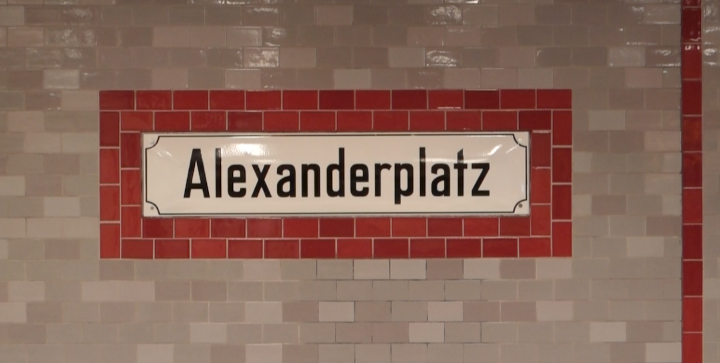
Welche Schrift ist das? (Alexanderplatz)
die wird es so als schrift nicht geben (und schon gar nicht als font). weil vermutlich seinerzeit mit schablonen handgefertigt.
du kannst aber nach ähnlichen suchen. zum beispiel eine, die hier vor einiger zeit quasi gemeinschaftlich entstanden ist:
Meine Freunde machen gerade dort im U-Bahnhof eine Ausstellung und ich wollte Ihnen bei der Typo behilflich sein,
sie brauchen das Wort Berlin (Alexanderplatz) - ich seh mich schon zeichnen.....
wie bereits angemerkt handelt es sich um eine typische Konstruktion wie man sie speätestens ab den 1920ern her kennt. So was gibt es auch auf Straßenschildern der Prä-Din1451-Ära und vielen anderen Orten.
Das kleine a ist allerdings extrem verschieden.  Es gibt hier vor Ort mindestens drei Versionen des kleinen a. Schleife geaht nach unten, wagrecht oder nach oben in den Schaft. Nur wenige Meter von hier findet man an einer Kreuzung an den verschiedenen Straßenschildern alle drei Versionen. Ich habe mich für die am strengsten geometrisch wirkende Version entschieden.
Recht dicht dran, wenn auch hier nicht ganz genau, möglicherweise sogar der DIN1451 Vorläufer der Preußischen Eisenbahnverwaltung nach Musterzeichnung IV 44 Ausgabe 3 - die vielleicht ja als Vorlage diente, und beim Zeichnen der Schablone fürs Emaillierwerk dann leicht verändert wurde: